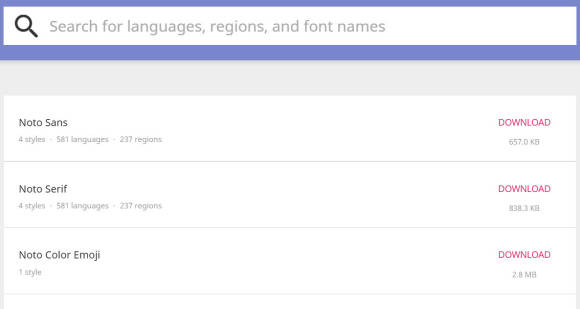
Googles neue Gratis-Schriftart kennt 800 Sprachen
Tot oder lebending: Googles Noto-Schriftart funktioniert jetzt mit allen Schriftarten der Welt.
Leere Viereckchen auf dem Bildschirm werden immer dann angezeigt, wenn ein bestimmter Zeichensatz einer anderen Sprache nicht richtig interpretiert werden kann. Die kryptischen Viereckchen haben auch einen Spitznamen: «Tofu». Abhilfe schaffen soll nun Googles fünfjähriges Projekt «No more tofu» («Nie mehr Tofu»), oder abgekürzt: «Noto». Die «Noto»-Bibliothek beinhaltet inzwischen mehr als 800 lebende und ausgestorbene Sprachen, davon 100 Schriftsysteme und 110'000 Zeichen. Dem Suchmaschinenriesen ginge es laut Blogbeitrag um die Erhaltung von Sprachen und Kulturen, auch wenn einige der Sprachen kaum mehr in Gebrauch seien.